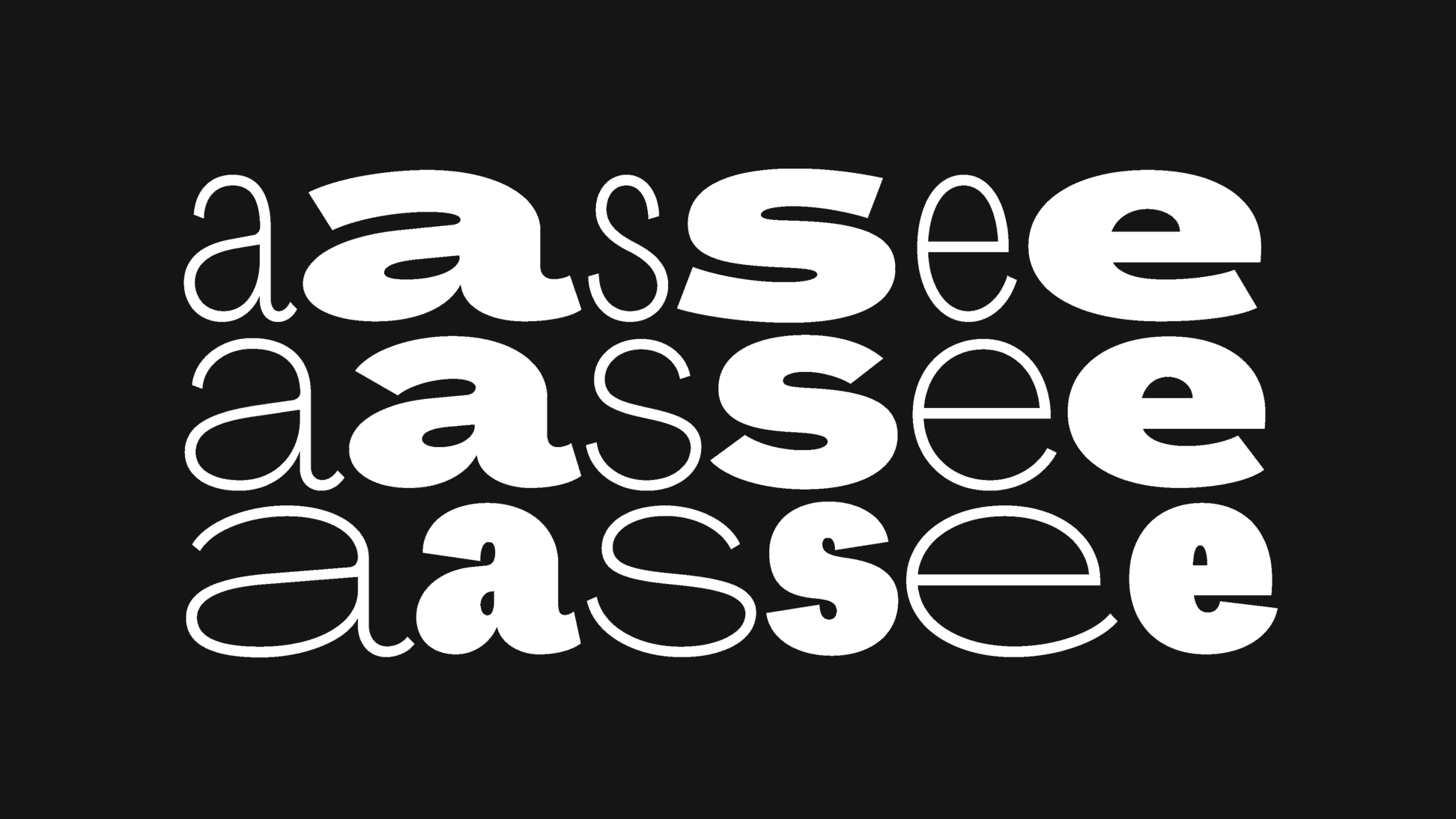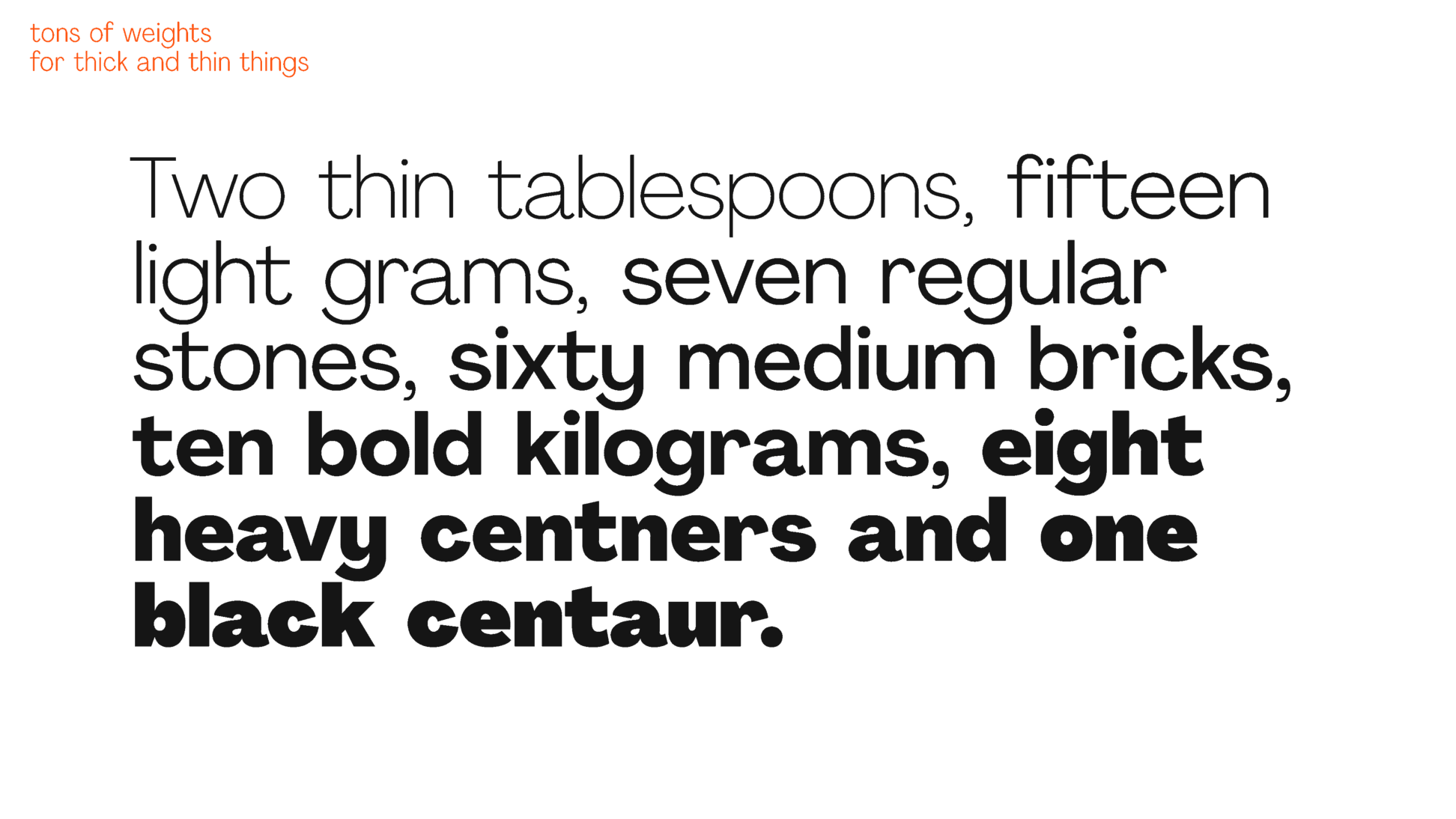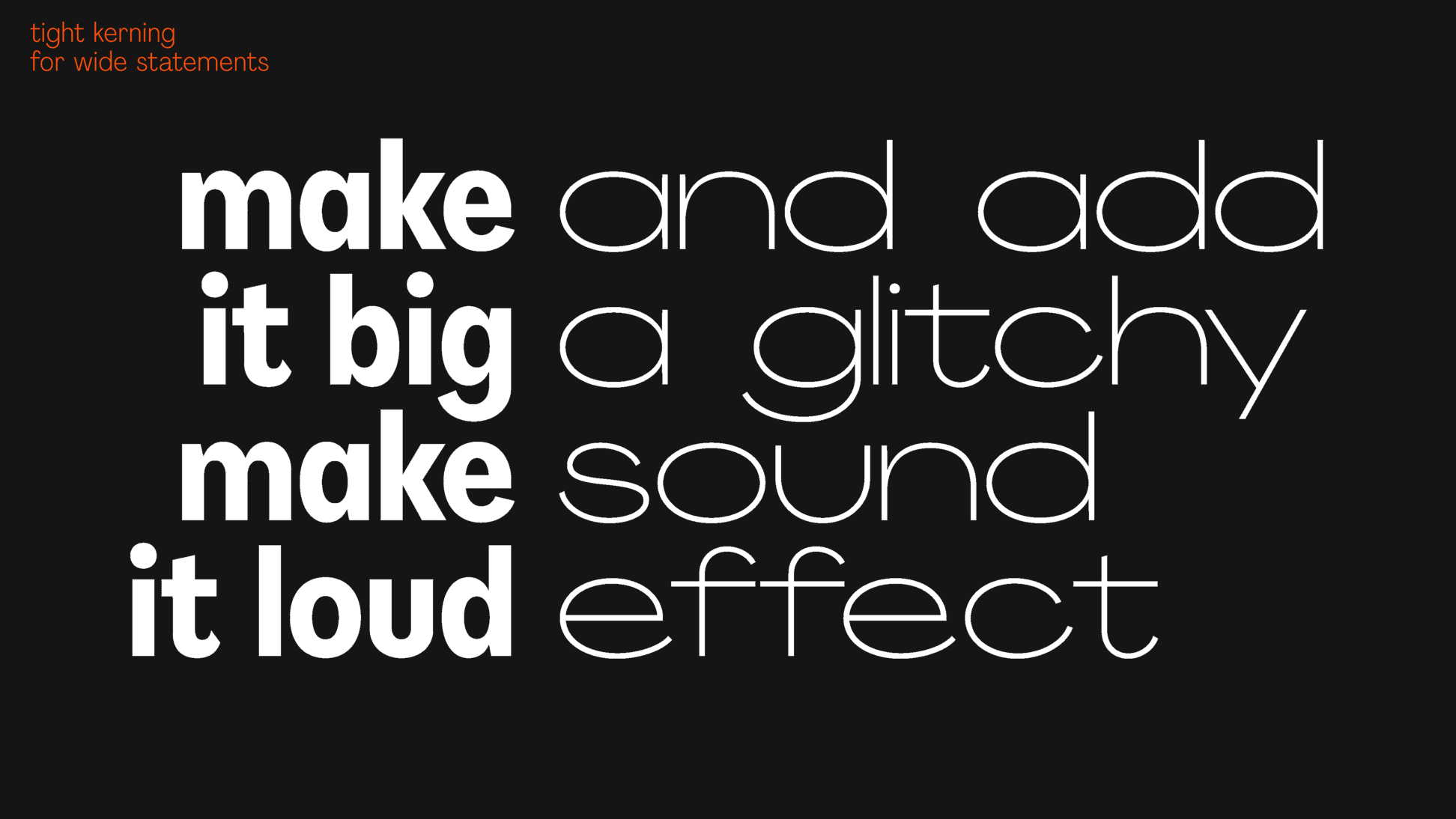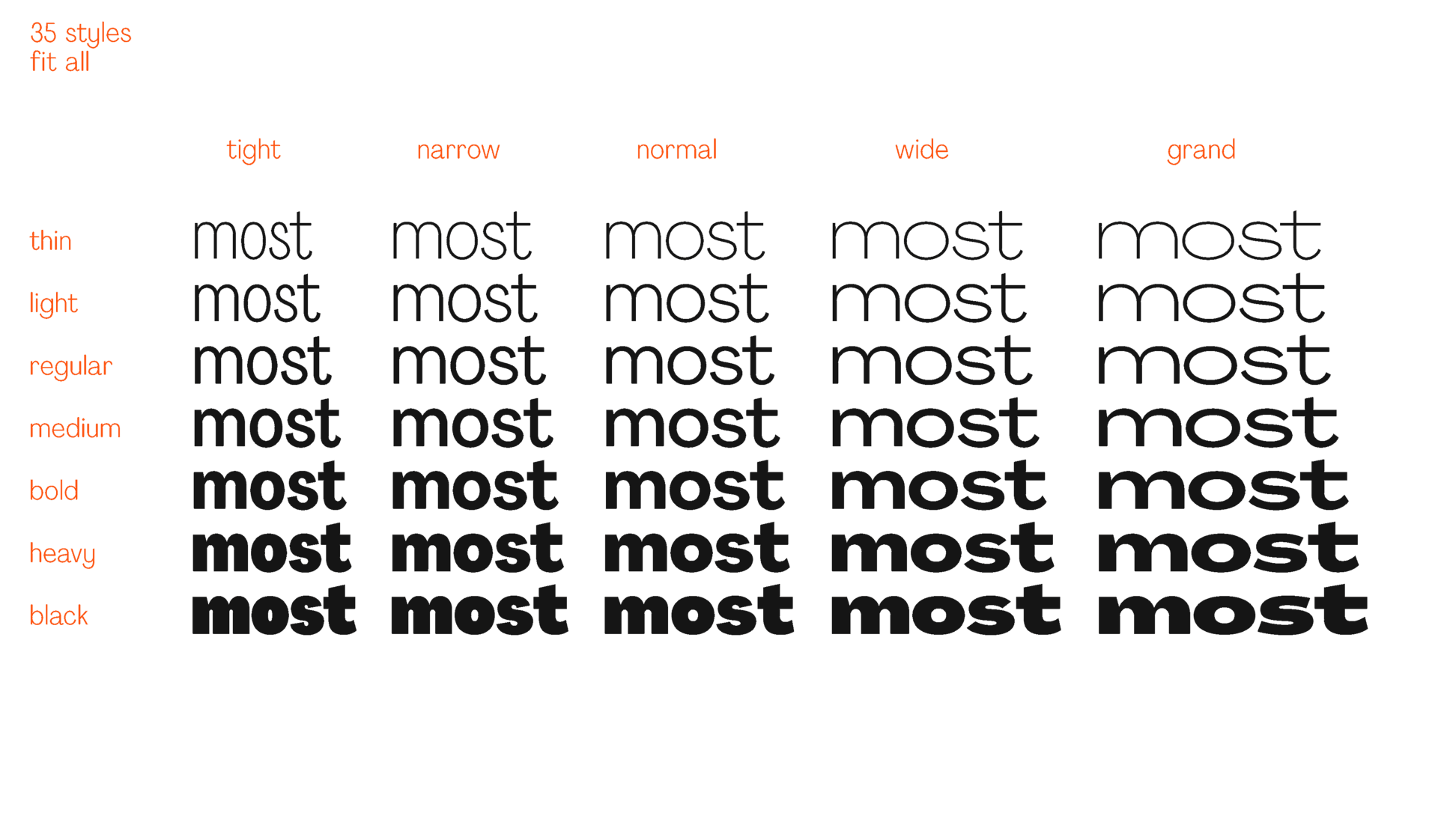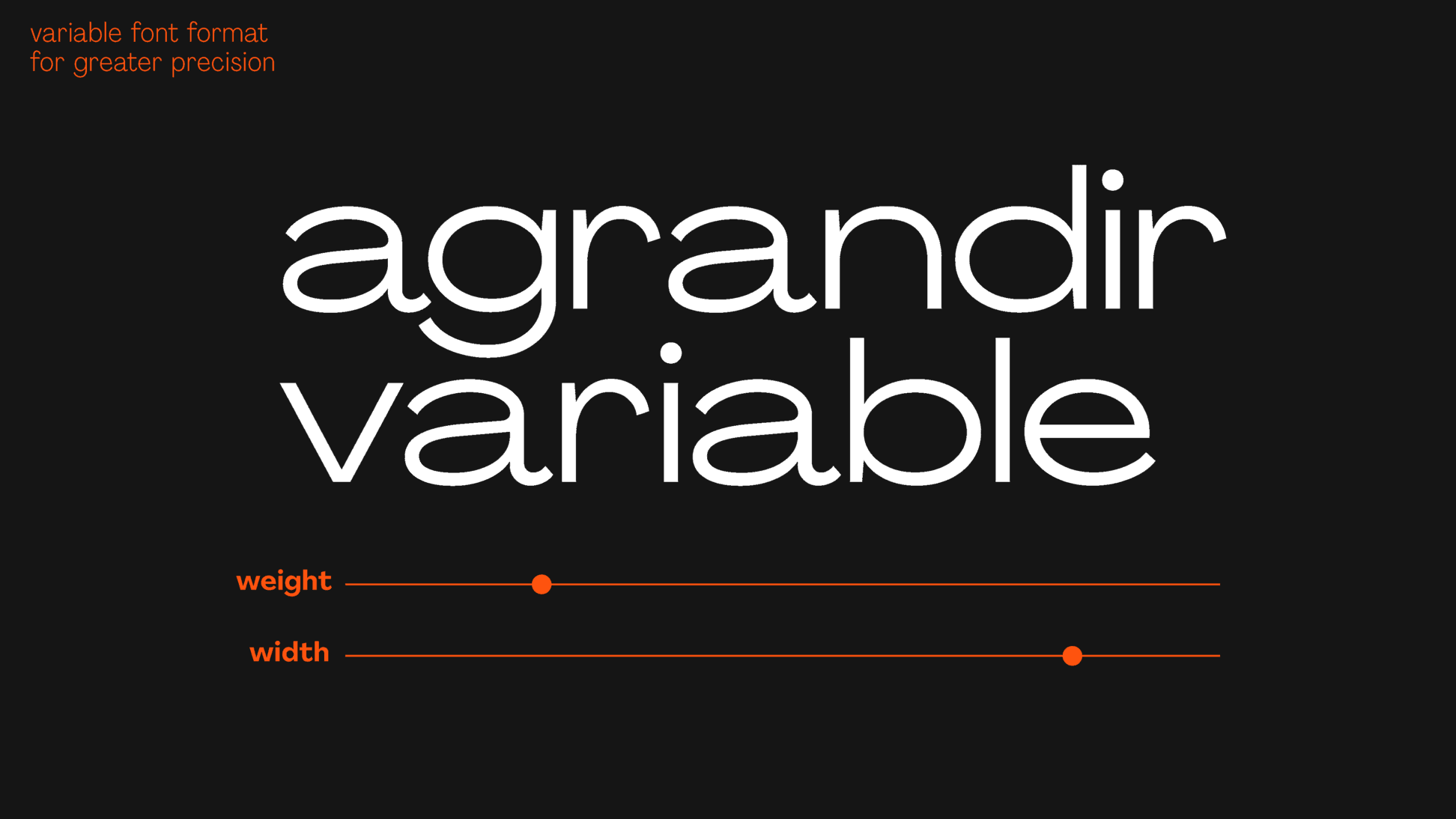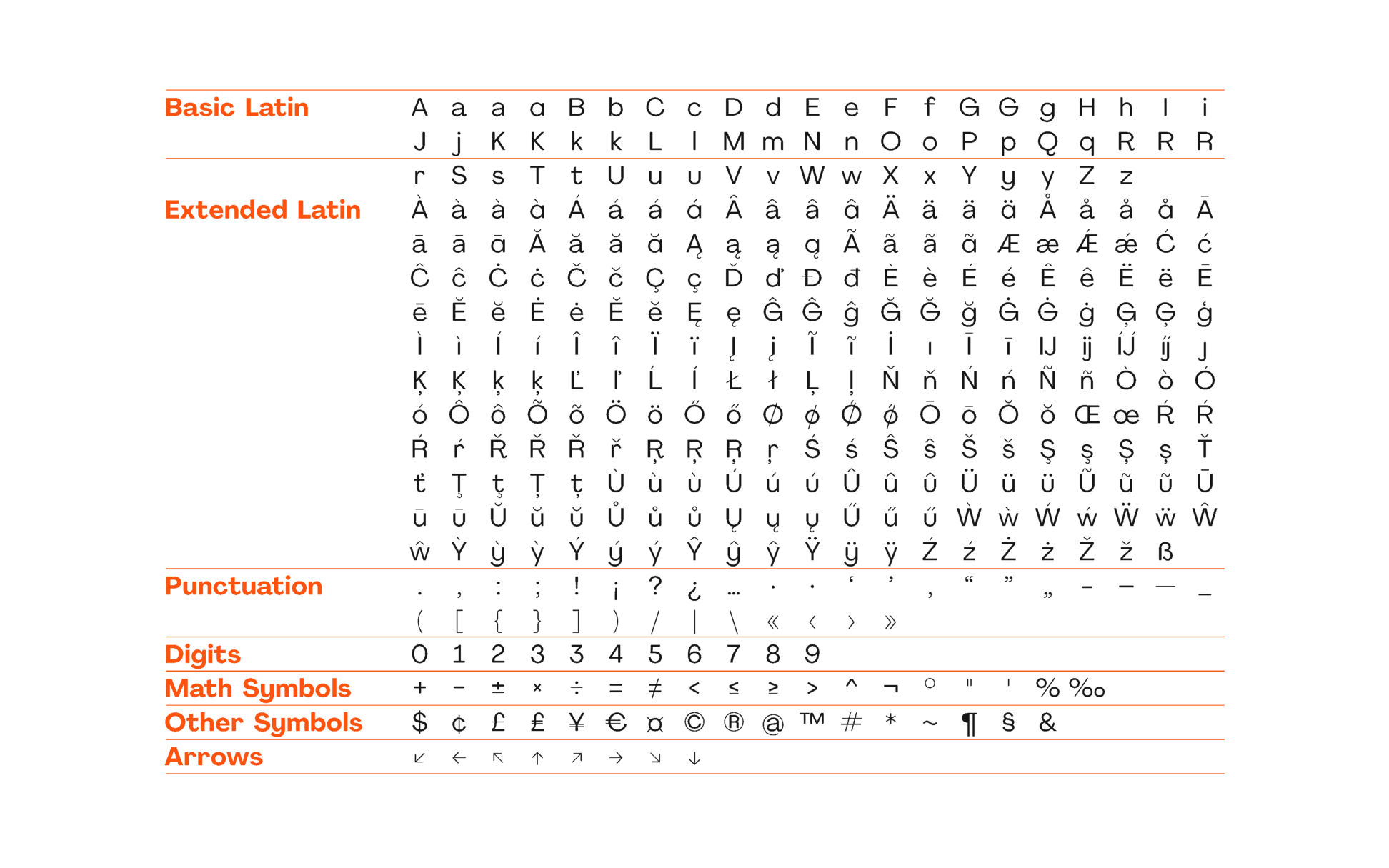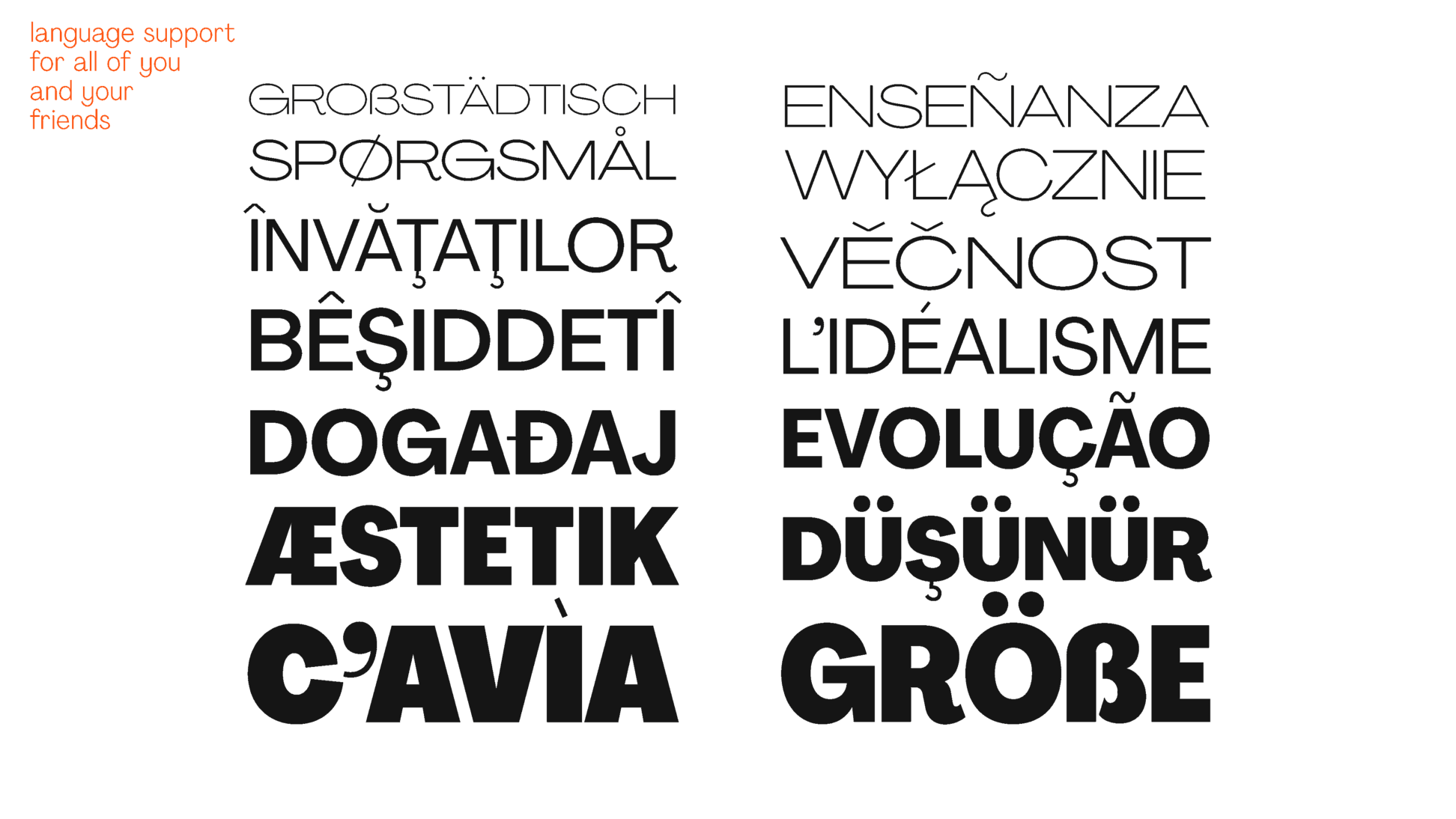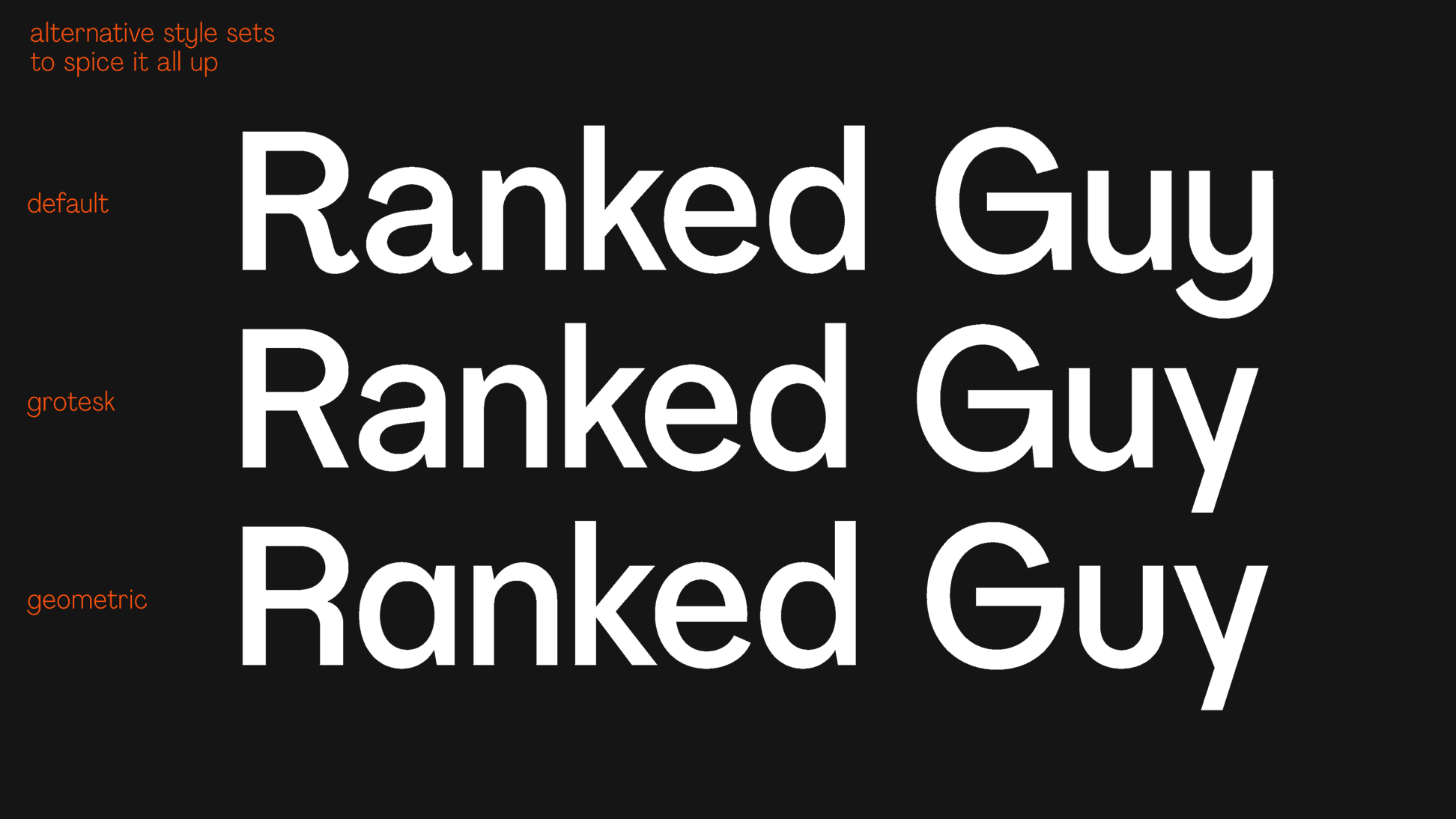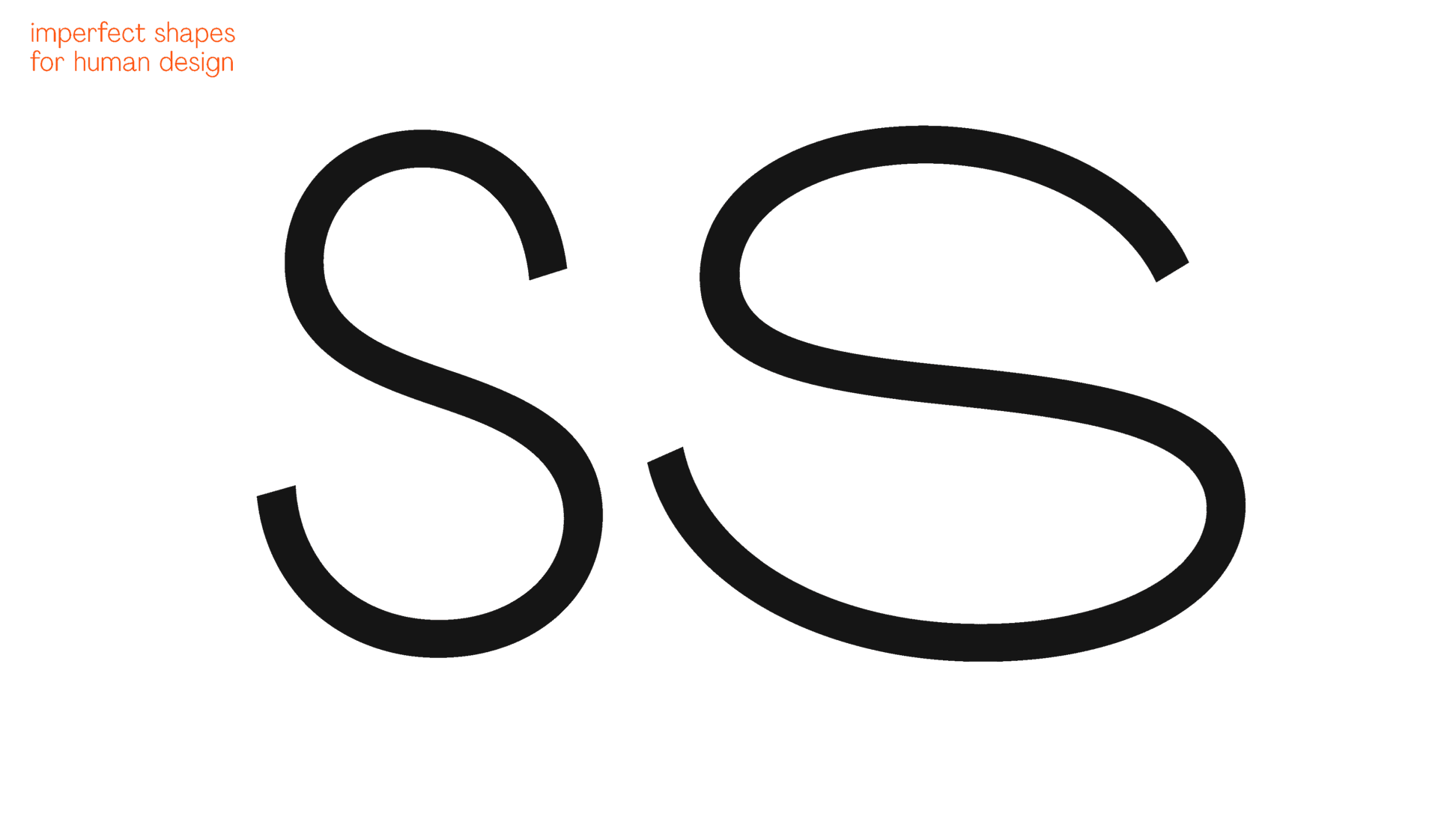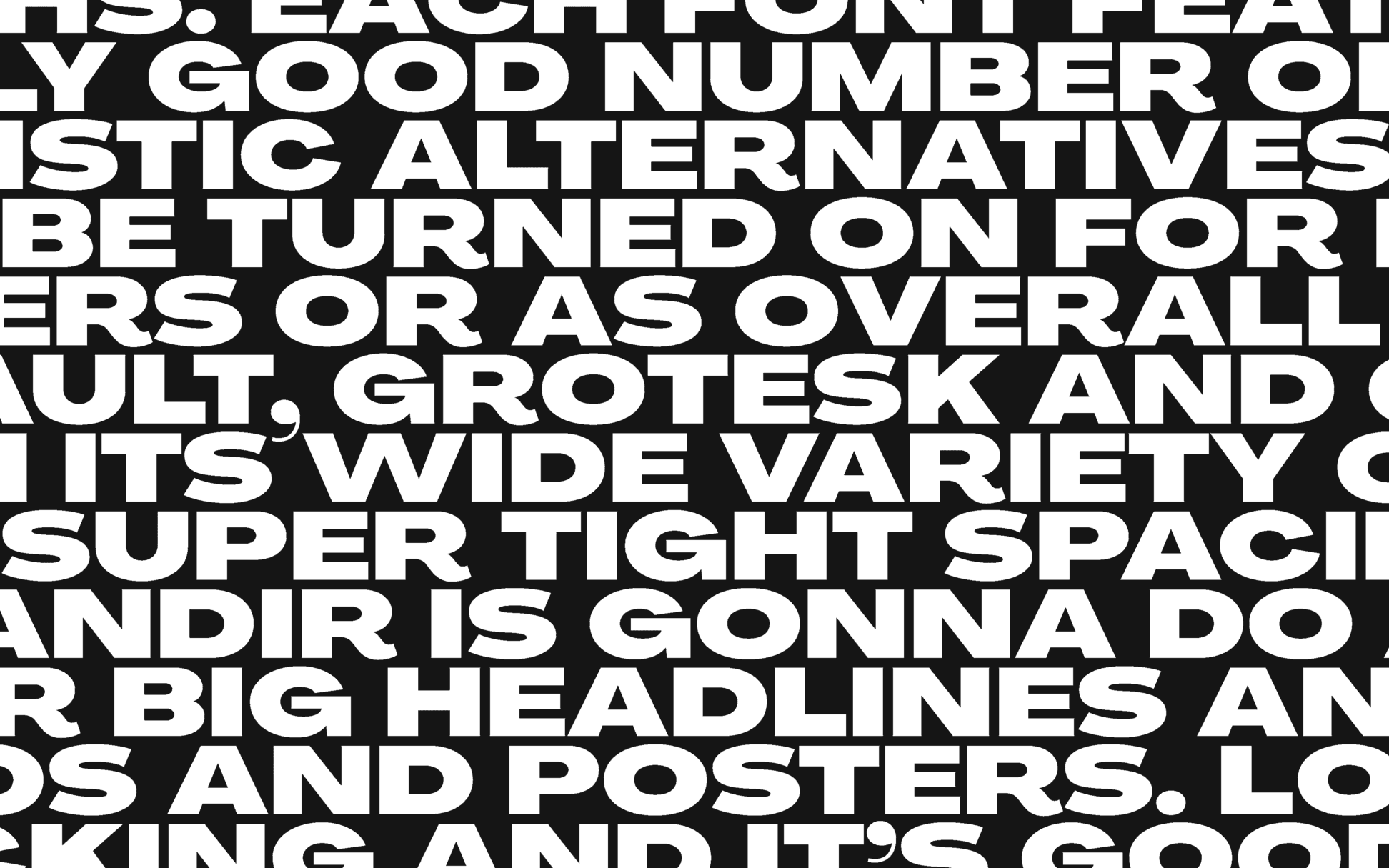
Agrandir Font Family là một font chữ hiện đại với vẻ đẹp hoàn hảo hoàn hảo. Bộ font bao gồm 74 phông chữ: 14 chiều rộng × 5 chiều rộng + 4 trọng lượng văn bản phụ.
Mỗi font chữ có một số lượng khá tốt các lựa chọn thay thế theo phong cách OpenType. Agrandir phù hợp với các tiêu đề, trang web, logo và áp phích kích thước lớn.
74 style với 417 glyphs, mỗi font Agrandir hỗ trợ 192 ngôn ngữ dựa trên latin. Được thiết kế bởi Alex Slobzheninov.